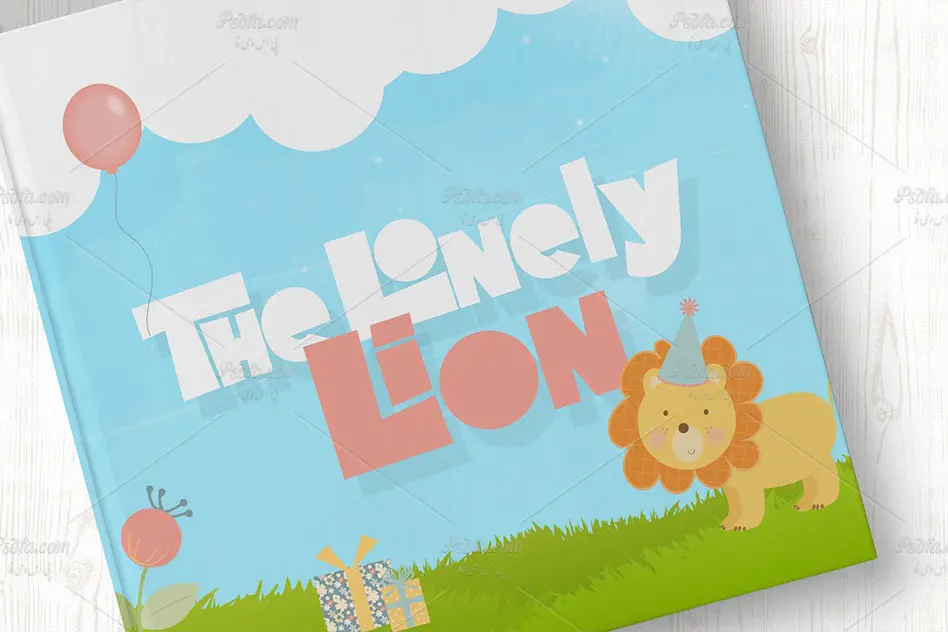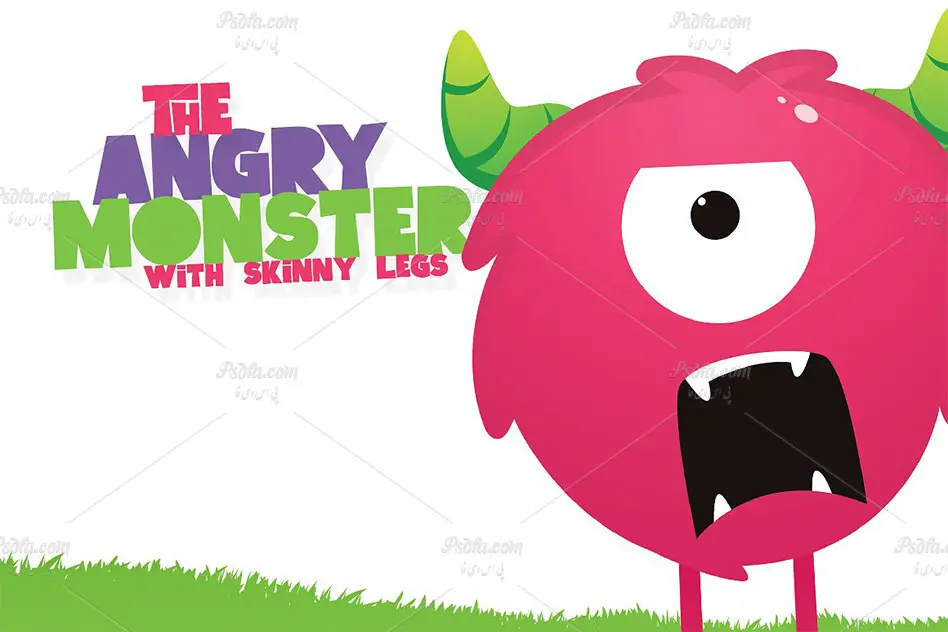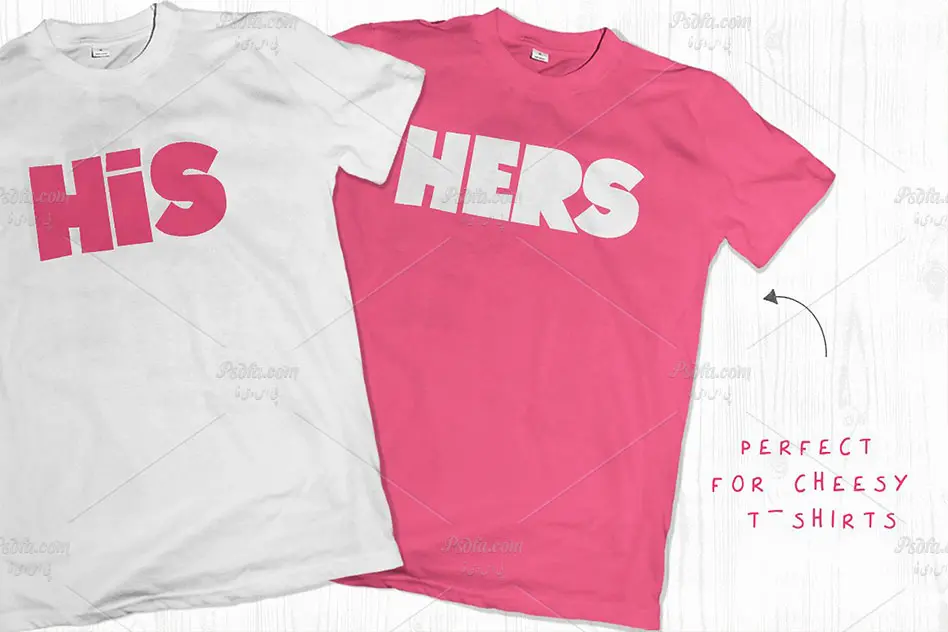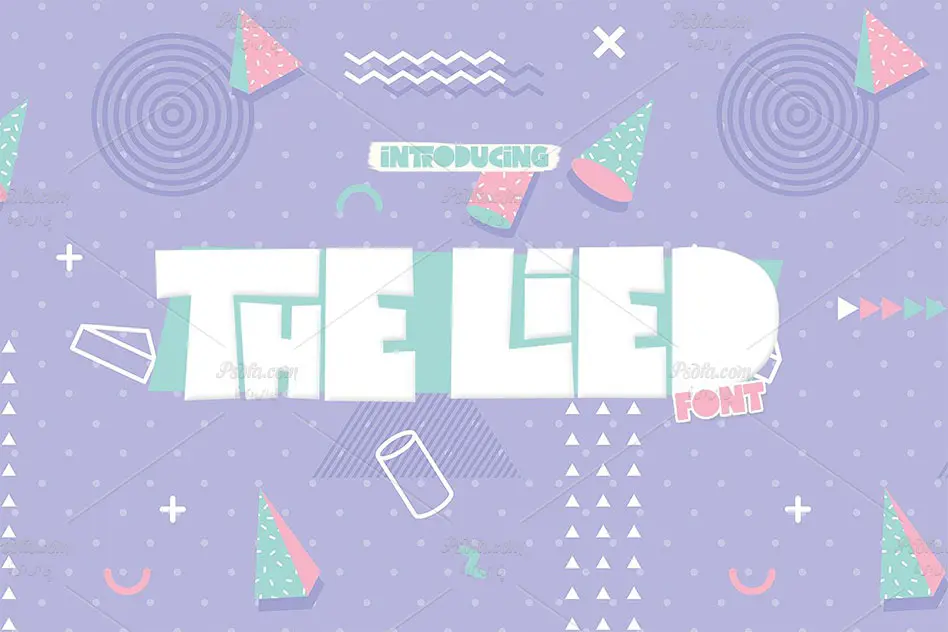
در این مطلب شاهد فونت انگلیسی فانتزی و کارتونی The Lied Typeface مناسب جهت استفاده در طرح های فانتزی و کودکانه می باشید. این فونت فوق العاده زیبا با فرمت های ttf , otf , woff , woff2 , svg و eot در سایت قرار گرفته است که پس از نصب آن در پوشه فونت های سیستم قادر به استفاده از آن در تمام نرم افزارهای گرافیکی و ویرایشگر متن از جمله نرم افزار فتوشاپ ، مجموعه نرم افزار آفیس و … می باشید. همچنین از فرمت های وب این فونت می توانید در طراحی وب سایت نیز استفاده کنید. از این فونت زیبا می توان در طراحی بر روی پارچه و لباس ، استفاده در تیتراژ برنامه های ویژه کودکان ، طراحی بر روی ظروف یک بار مصرف ، طراحی بسته بندی محصولات ، طراحی بر روی قاب و کاور موبایل و … استفاده نمود.